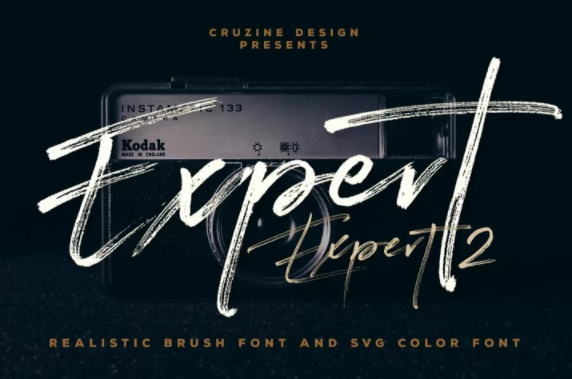
[Fontbundles] Expert Brush & SVG Font (2022)
Шрифт в стиле кисти или гранж для ваших новых проектов.
Отлично подходит для гранжевых или художественных проектов!
Шрифт в стиле кисти или гранж для ваших новых проектов.
Отлично подходит для гранжевых или художественных проектов!